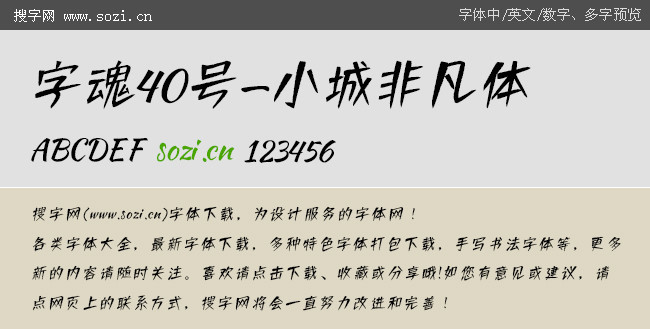
字魂40號(hào)-小城非凡體
搜字網(wǎng)提供一款字魂40號(hào)-小城非凡體中文字體下載,該字體是一款硬筆手寫字體,該字體包含6763個(gè)中文、字母、 符號(hào)和數(shù)字,具有現(xiàn)代、簡(jiǎn)約、帥氣、童真、創(chuàng)意 的風(fēng)格,可以滿足您設(shè)計(jì)上的各種需求,該字體主要用于H5、包裝、店鋪、廣告、企宣、媒體、社交 等場(chǎng)景。